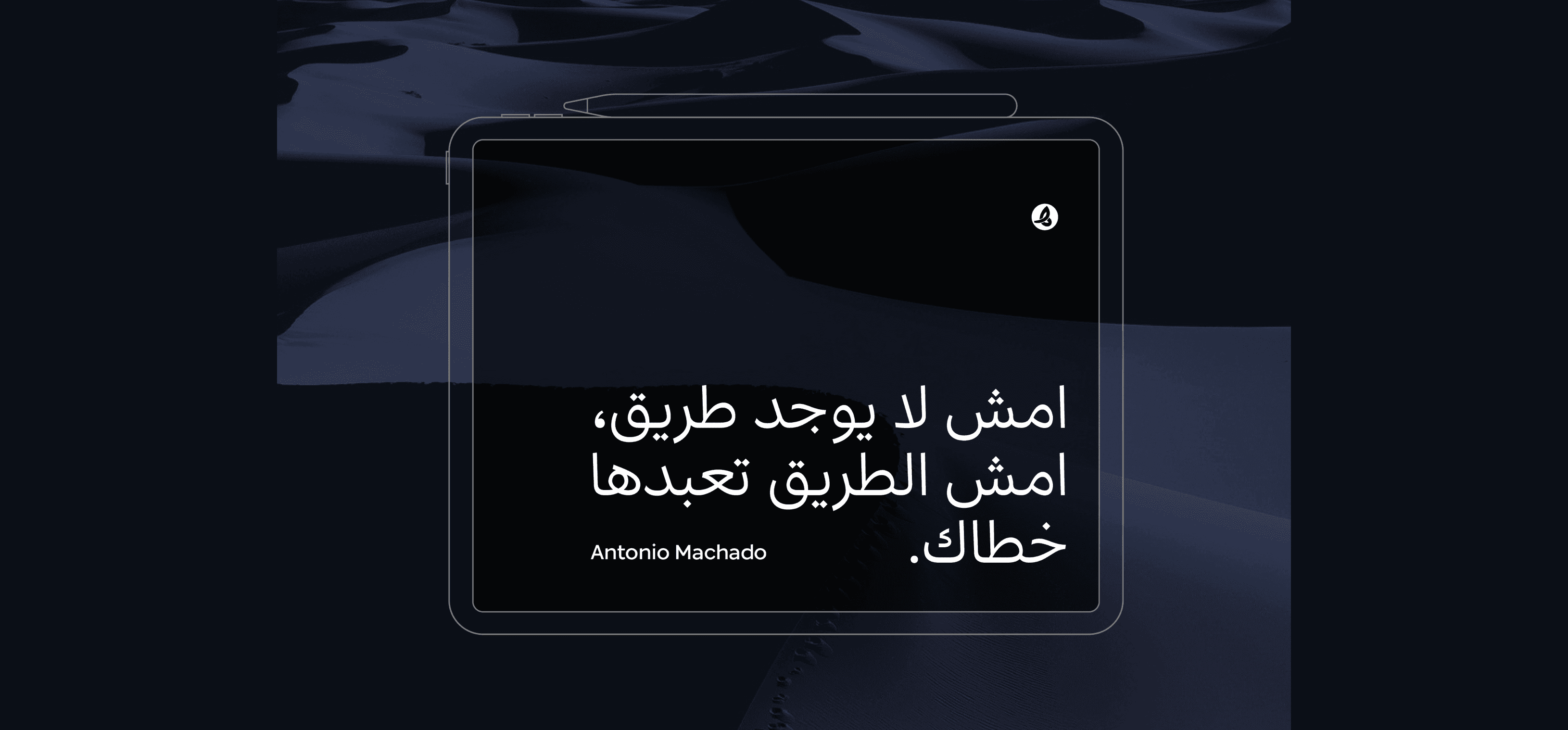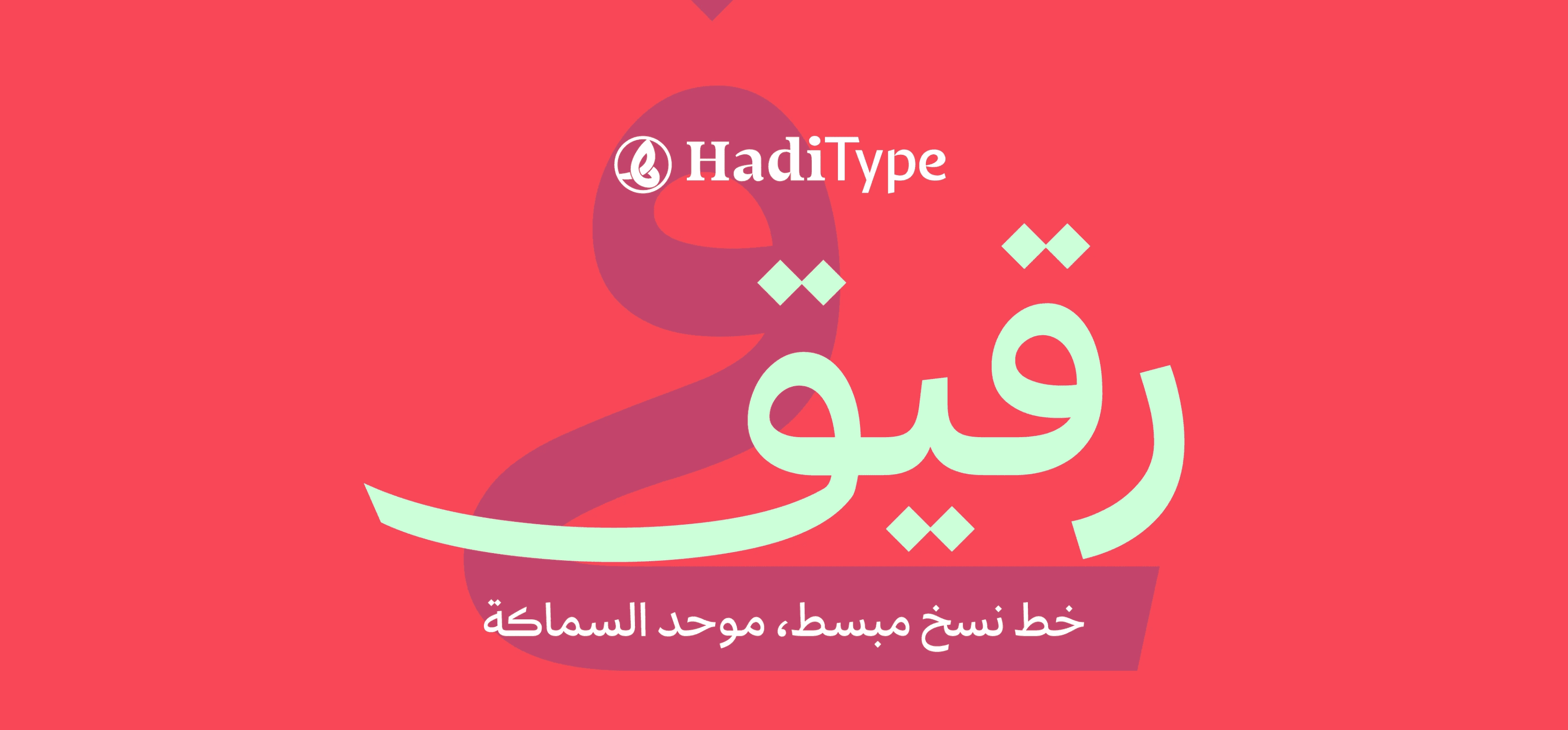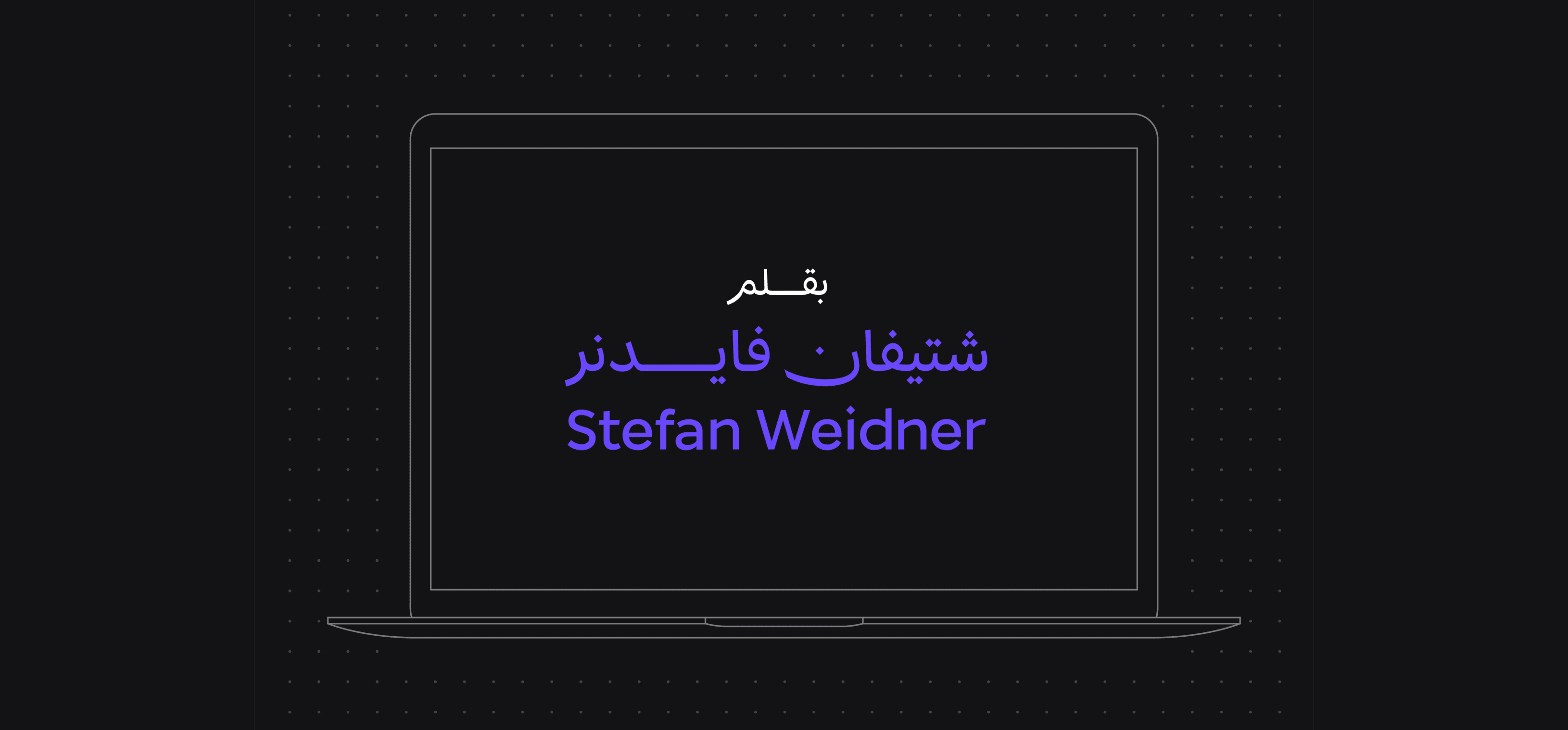
خط HT رقيق – HT Rakik Font
خط نسخي مبسّط أحادي العرض، يتميز بنقاء تصميمه وجوهره العربي الأصيل، ما يجعله مثاليًا لتعزيز الكتابة العربية في العصر الرقمي.
يدعم لغات متعددة مثل العربية، الفارسية، الأردية، الجاوي، واللاتينية الأساسية، مما يمنحه مرونة عالية في الاستخدام.
يتوفر الخط بخمسة أوزان متدرجة، تُتيح للمصممين حرية التوازن بين الأناقة والوضوح في مختلف المشاريع الطباعية والرقمية.